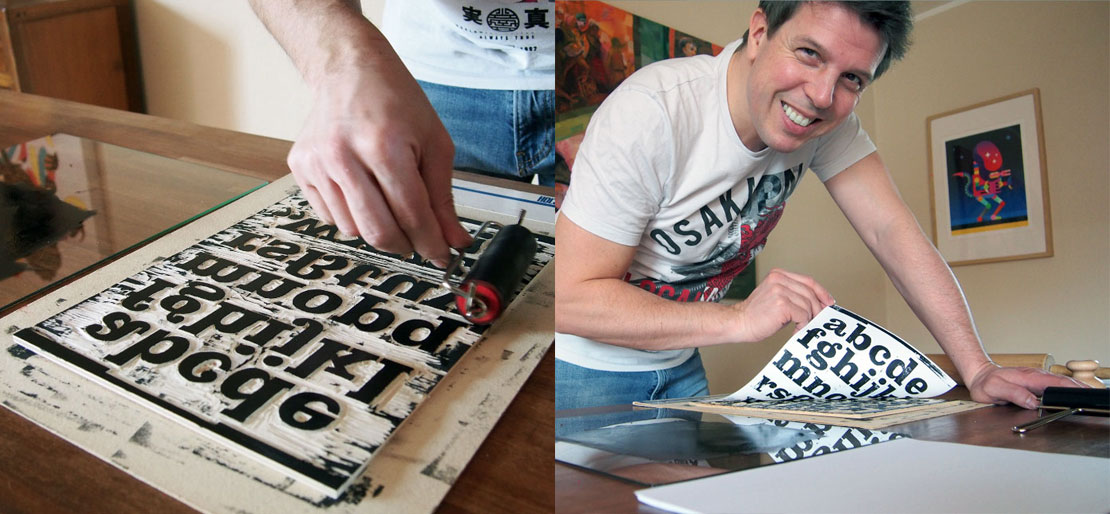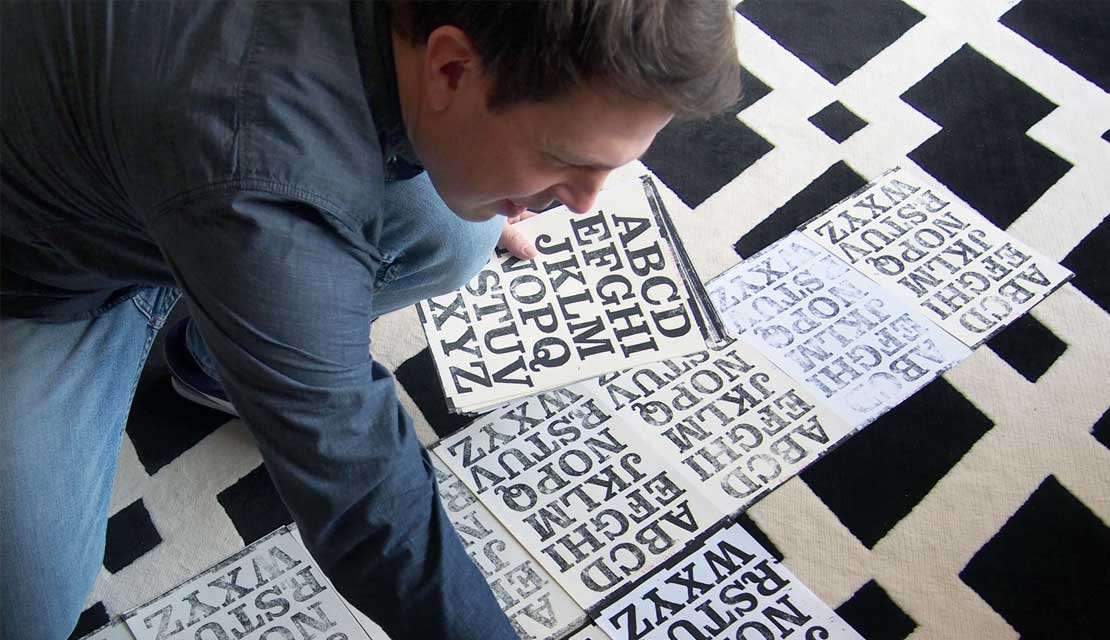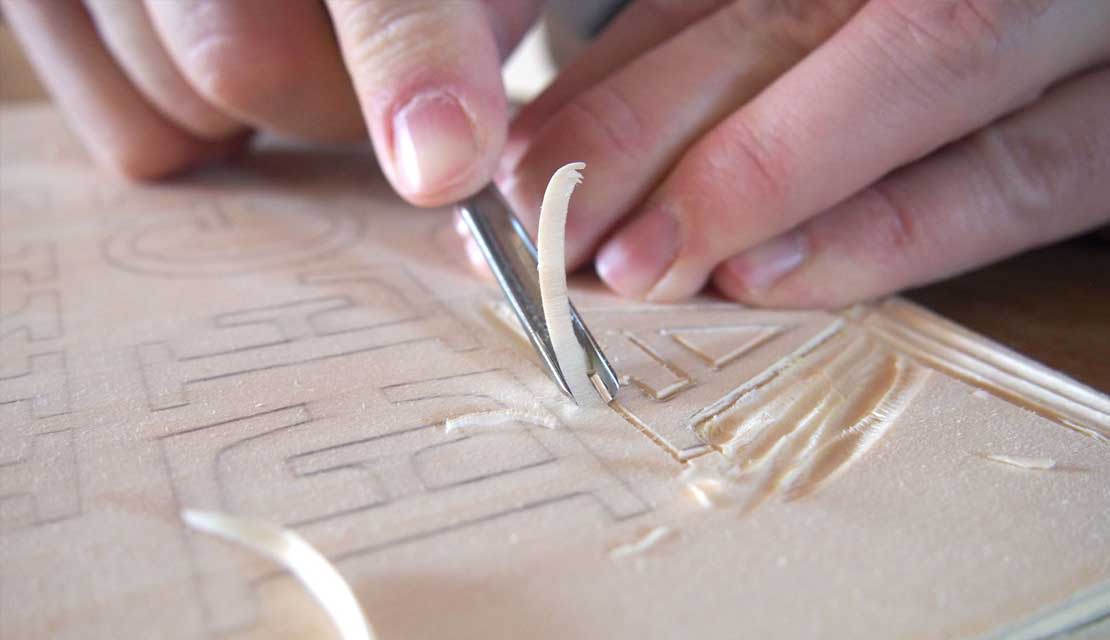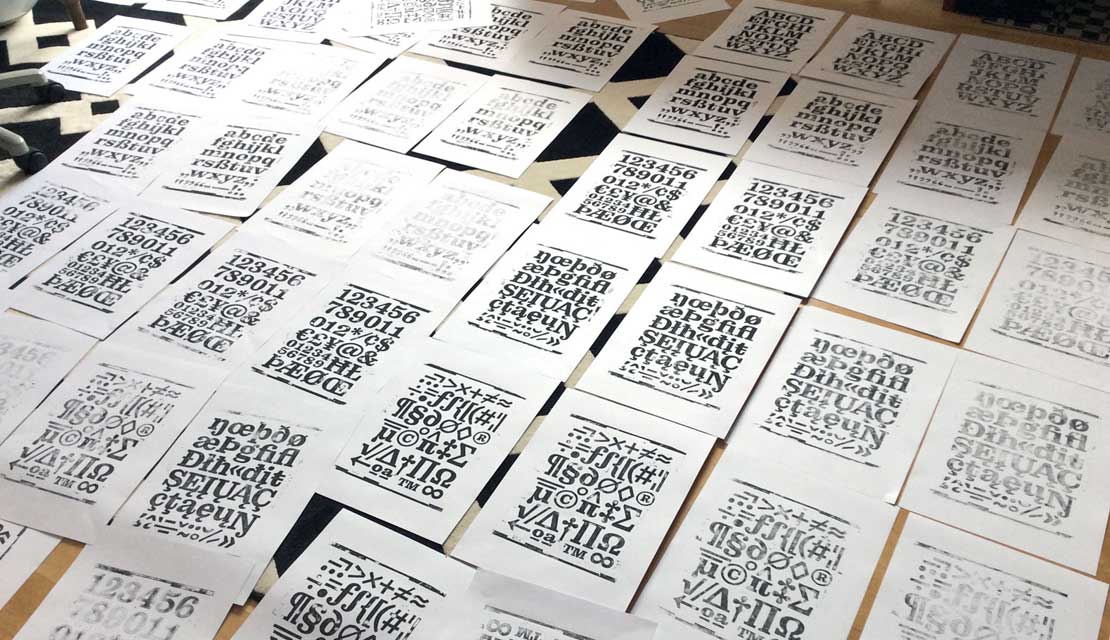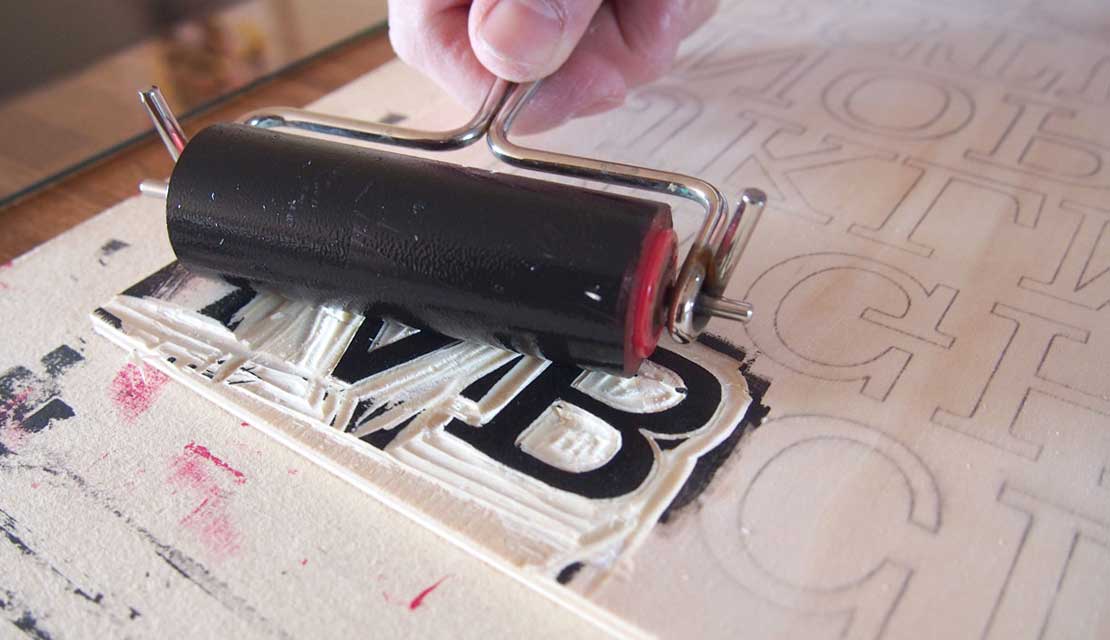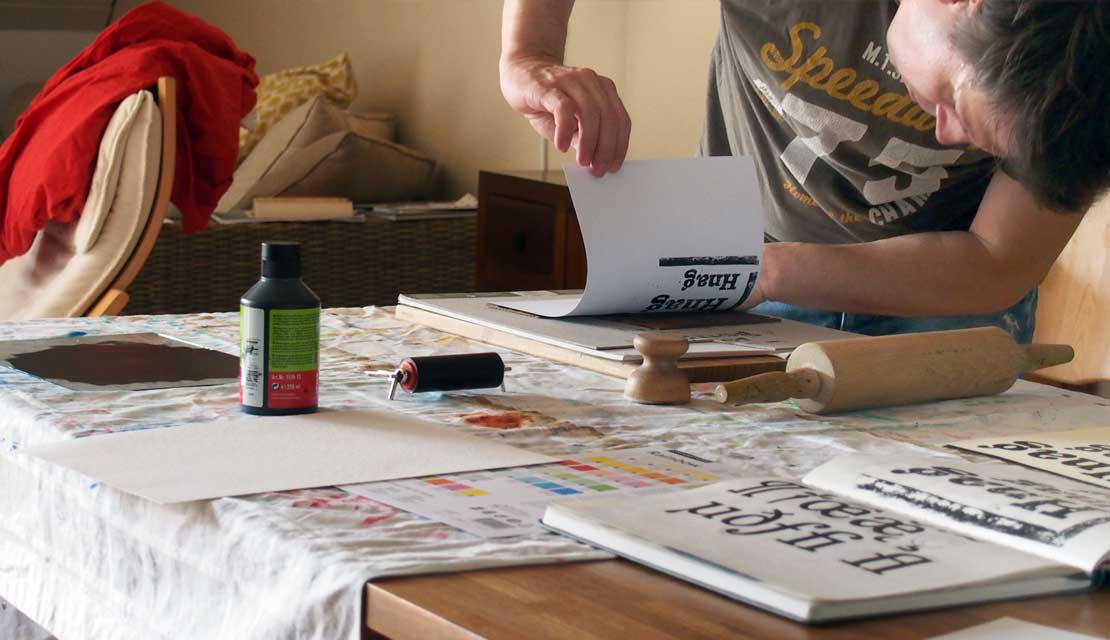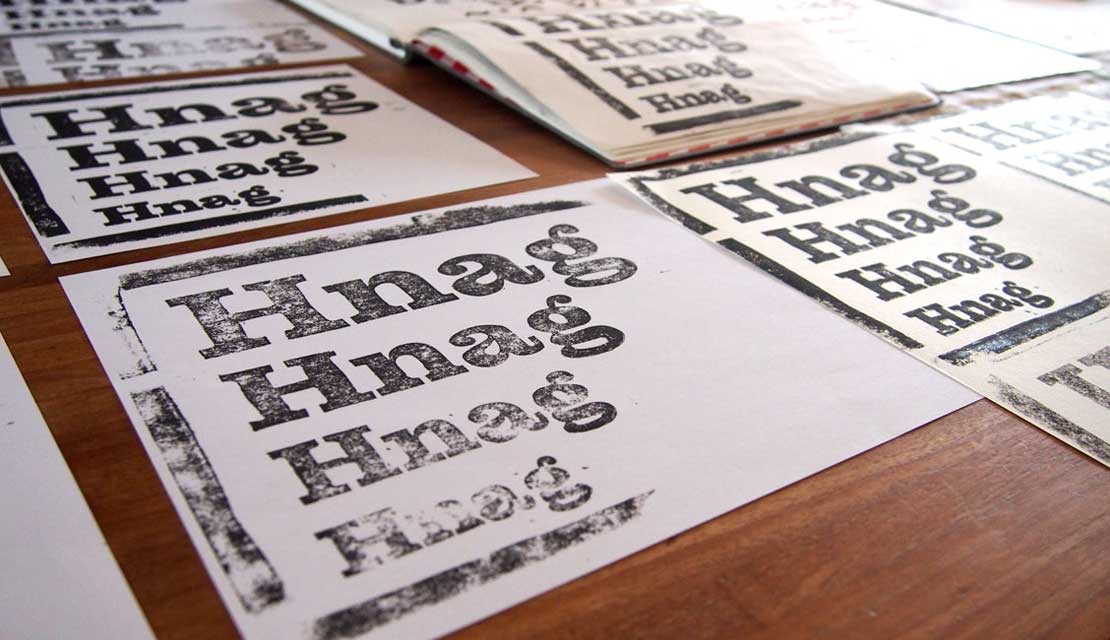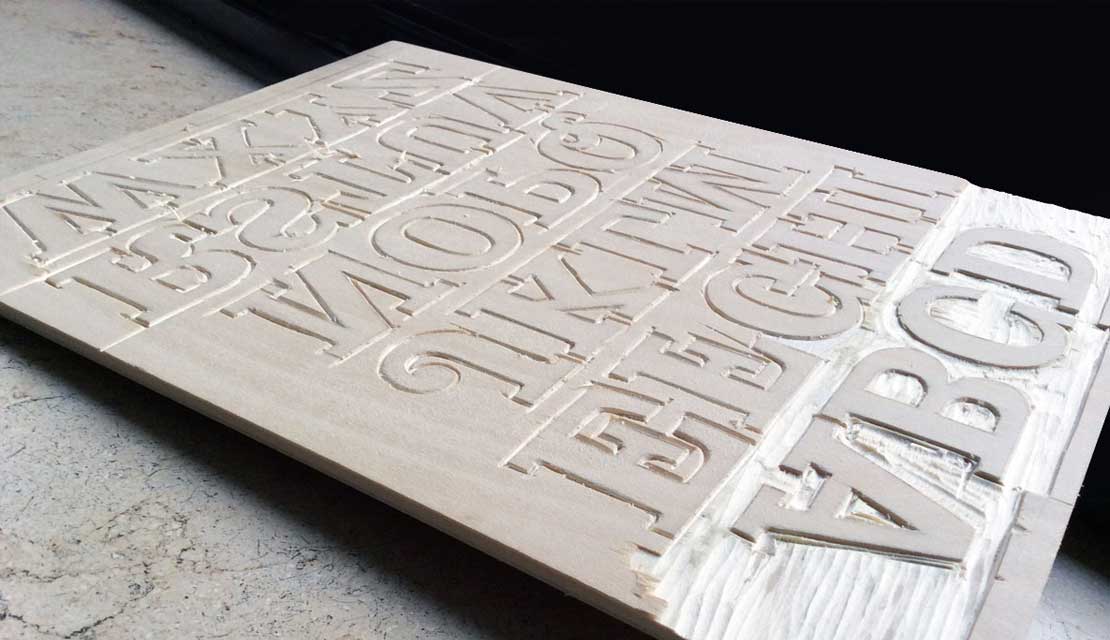
Schriftart »Kontiki« simuliert handgemachten Holzdruck
Der Charme von manuell hergestellten Drucksachen hat in der heutigen Zeit einen besonderen Wert. Die Schriftart Kontiki simuliert digital einen handgemachten Holzdruck.
Die Schriftart ermöglicht es, ein Druckbild ähnlich einem traditionellen Holzschnitt zu schaffen, ohne dass man dabei etwas dem Zufall überlassen muss.
Für die Erstellung der Schrift hat der Kölner Designer Felix Braden 193 Glyphen per Hand aus fünf Holzplatten geschnitten und manuell gedruckt. Aus unzähligen Testdrucken wurden die interessantesten vier ausgewählt und digitalisiert um die unterschiedlichen Schnitte von Kontiki zu erstellen.
Zu jedem der 560 Zeichen bietet »Kontiki« vier verschiedene Druckbilder und gibt dem Designer die Möglichkeit zu variieren und ein bewegtes Schriftbild nach seinen eigenen Vorstellungen zu schaffen.
Die Entstehung der Schrifart
Inspiriert von den handgemachten Drucken seiner Frau entschied sich Felix Braden einen kompletten Schriftsatz in Holz zu schneiden und manuell zu drucken. Er begann bei einer seiner Lieblingsschriften – Century Schoolbock – den Wechselstrich zu reduzieren, um auf dieser Basis eine Clarendon zu zeichnen. Ein leichter und ein fetter Schnitt wurden digitalisiert, um daraus einen halbfetten Schnitt zu interpolieren und in Holz zu schneiden.
Nach Testläufen mit verschiedenen Materialien und Größen, entschied er sich für einen Holzschnitt mit einer Schriftgröße um 150 Punkt und schnitt einen kompletten Schriftsatz auf fünf Druckplatten. Auch beim Papier waren viele Testdrucke erforderlich. Jede Platte wurde in einer Auflage von 30 Stück gedruckt und jeweils vier Qualitäten für die Digitalisierung gewählt: Ein normaler Druck, einer mit halber Kraft und zwei Folgedrucke ohne neuen Farbauftrag.
Danach wurde der komplette Satz gescannt und alle Glyphen eines Druckgangs in einer Bilddatei gesammelt. Um einfache Pfade für die Vektorisierung (mit Georg Seiferts Glyphs-Erweiterung »Trace Image«) zu bekommen, mussten die Bilder mit einem Weichzeichner und dem Helligkeit-interpolieren-Filter in Photoshop bearbeitet werden – denn in einem gut funktionierenden Font sollten die einzelnen Glyphen nicht mehr als 1000 Punkte und nur gerade Konturlinien besitzen. Danach wurden alle Zeichen in Glyphs bearbeitet, optimiert und die Fonts generiert.
Wie die Schrift entstanden ist, kann man in dieser Foto-Galerie sehen:
Umfang und Features der Schrift
»Kontiki« bietet vier Schnitte mit unterschiedlichem Druckbild als separate Schriftdateien. Die Pro Version vereint alle 2240 Zeichen in einer Schriftdatei und enthält die einzelnen Varianten als sogenannte »Stylistic Alternates«. Außerdem ermöglicht das Opentype-Format eine zufällige Variation der Glyphen mit unterschiedlichem Druckbild.
Die Schriftart enthält Versal- und Mediävalziffern für Fließtext und Tabellensatz sowie mathematische Zeichen und gängige Währungszeichen in allen vier Schnitten. Um den Bedürfnissen der globalen Kommunikation gerecht zu werden bietet Kontiki eine umfangreiche Sprachunterstützung für alle west-, ost- und mitteleuropäischen Sprachen